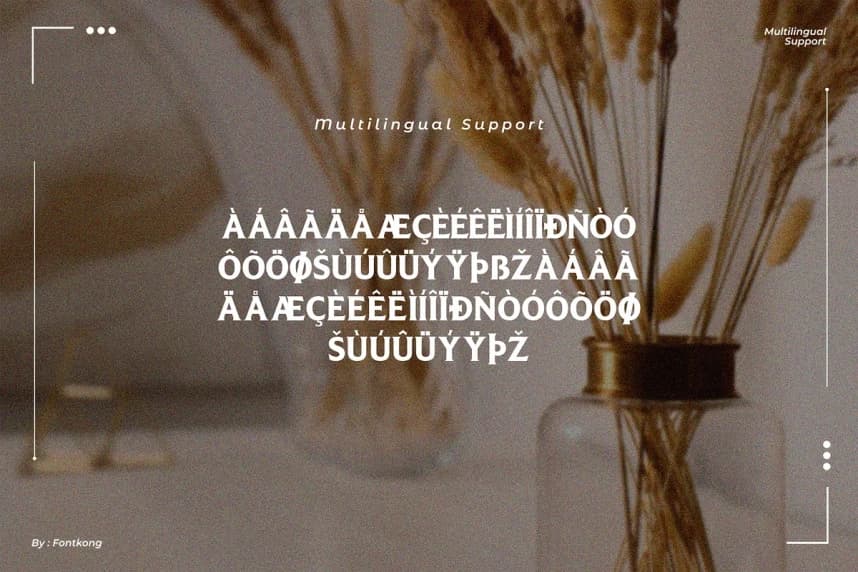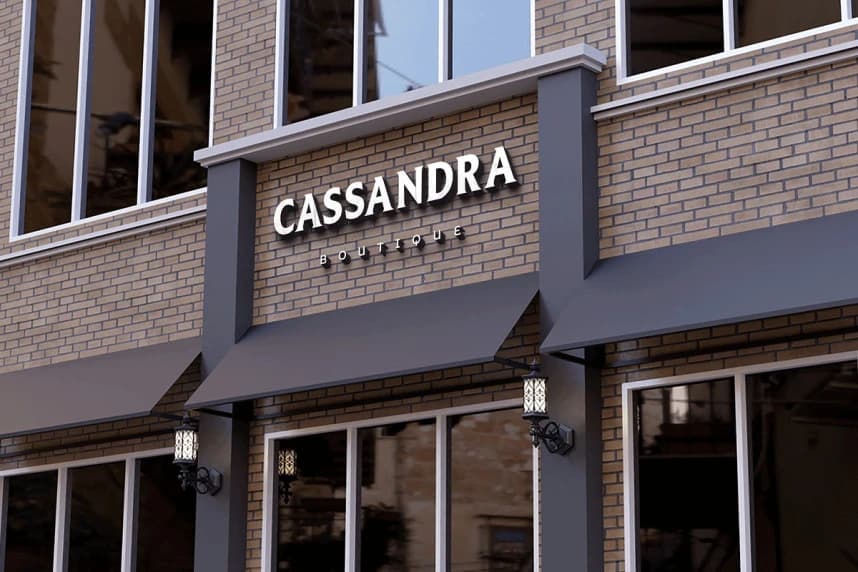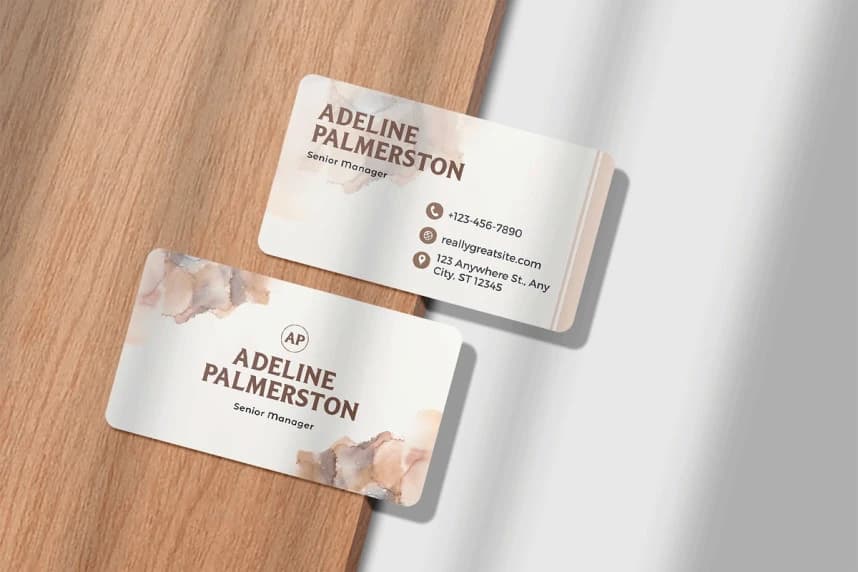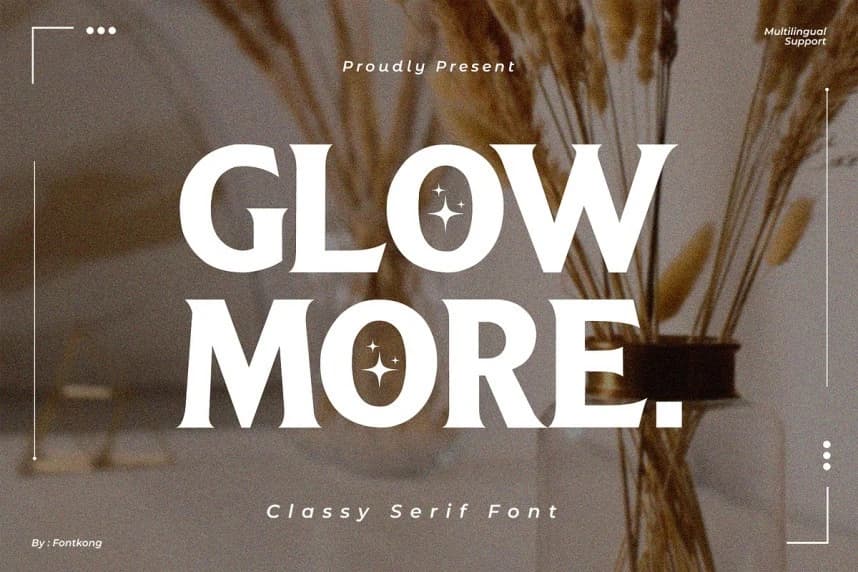
Glowmore, zamansız stil ile modern bir şıklığı bir araya getiren zarif bir serif yazı tipidir. Marka oluşturma, davetiyeler, editoryal düzenler ve lüks ambalajlar için idealdir; bu yazı tipi zarafet ve profesyonellik hissi uyandırır.
Glowmore, zamansız stil ile modern çekiciliği birleştiren şık bir serif yazı tipidir. Markalaşma, davetiyeler, editöryal düzenler ve lüks ambalajlar için idealdir. Bu yazı tipi zarafet ve profesyonellik hissi uyandırır.